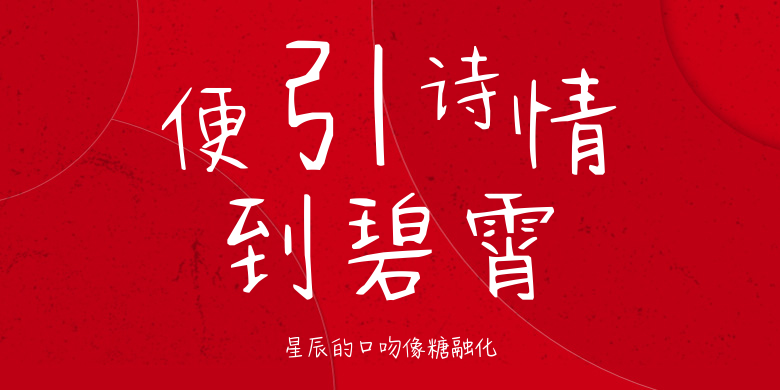
星辰的口吻像糖融化
星辰的口吻像糖融化,这款字体结构工整、笔画清晰,兼顾美观与易读性,适用于标题、正文、海报、包装、LOGO 等多种场景。字形优雅稳定,风格百搭耐看,适配日常排版与创意设计,让文字呈现更舒适、更具质感。星辰的口吻像糖融化一笔一画,皆是细节,以均衡的比例、流畅的线条打造舒适视觉体验,字形端正大气,风格简约现代。无论是商业设计、品牌宣传还是日常排版,都能轻松驾驭,让文字更有格调与力量。星辰的口吻像糖融化字体下载。